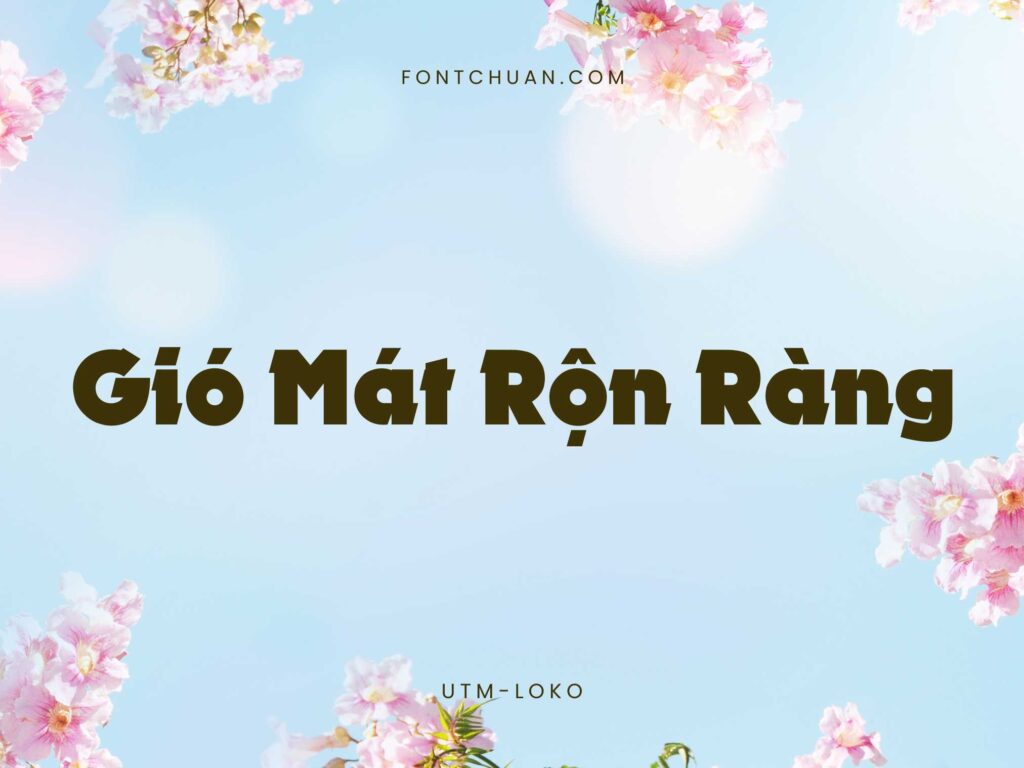
UTM Loko là một font chữ sáng tạo với phong cách mạnh mẽ, phù hợp cho các thiết kế hiện đại và phá cách. Font này mang đến cảm giác độc đáo với các đường nét cứng cáp, tạo sự thu hút đặc biệt trong các thiết kế đồ họa. Font đã được Việt hóa bởi Thiên Minh, hỗ trợ đầy đủ tiếng Việt cùng hơn 200 ngôn ngữ khác, giúp mở rộng khả năng sử dụng. Thành viên của Font Chuẩn đã sưu tầm và giới thiệu font này nhằm đáp ứng nhu cầu bạn đọc, cung cấp nguồn tham khảo chất lượng và ứng dụng thực tế vào các dự án thiết kế
Về đặc điểm thiết kế, UTM Loko có các đường nét chắc chắn, bố cục mạnh mẽ và tạo cảm giác cá tính. Font này phù hợp với nhiều ứng dụng như thiết kế logo, tiêu đề, poster, biển hiệu và các dự án sáng tạo khác. Các ngành nghề như quảng cáo, công nghệ, giáo dục và thiết kế thương hiệu có thể tận dụng font này để tạo nên sự khác biệt và thu hút trong các ấn phẩm thiết kế